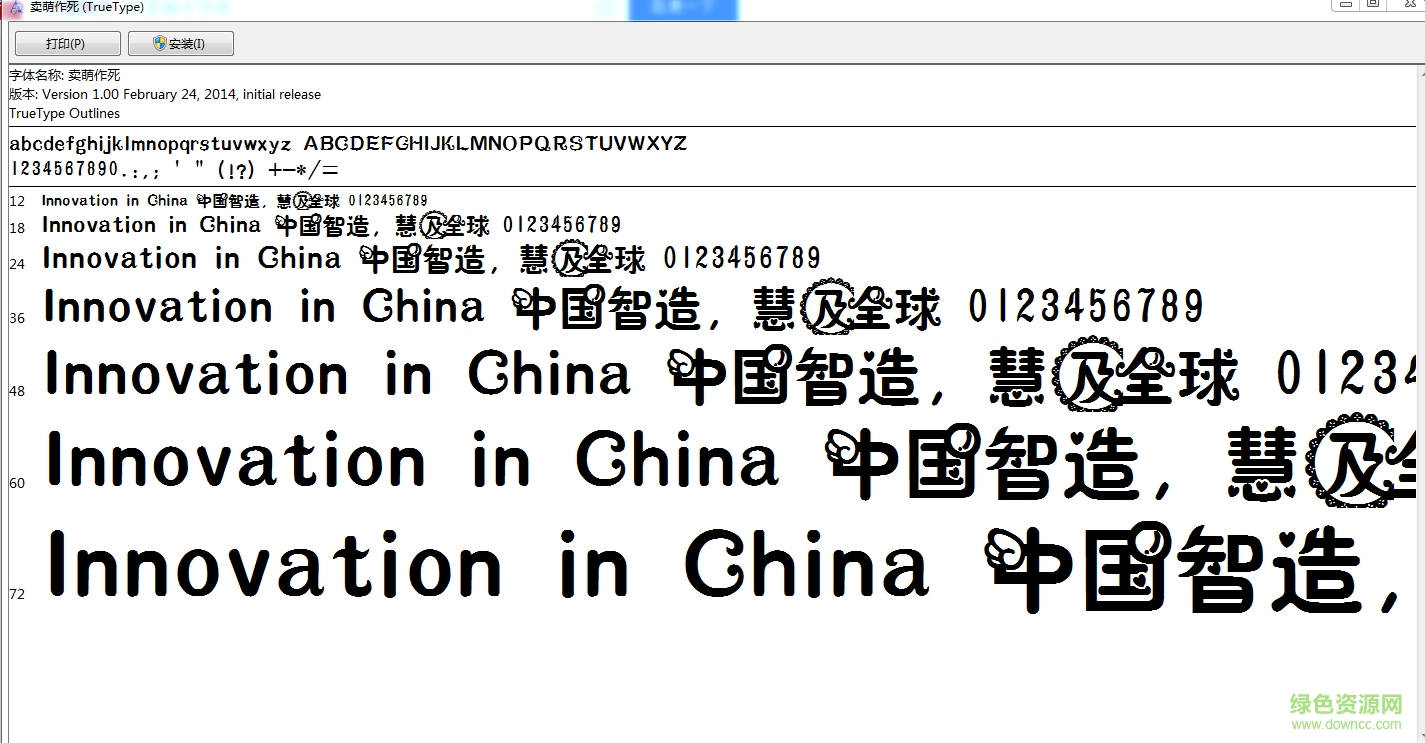
賣萌字體
賣萌作死字體是一款筆墨濃重的簡體字體,字體粗黑,結(jié)構(gòu)端正,線條圓潤可愛,還帶有個(gè)性十足的花邊、小拳頭,心形等元素,有興趣的小伙伴不妨在綠色資源網(wǎng)下載!
賣萌作死字體介紹
賣萌作死字體是一款效果出眾的簡體中文漢字,適用于廣告設(shè)計(jì)、藝術(shù)創(chuàng)作、平面設(shè)計(jì)、印刷包裝等應(yīng)用,有喜歡的朋友可免費(fèi)下載收藏。